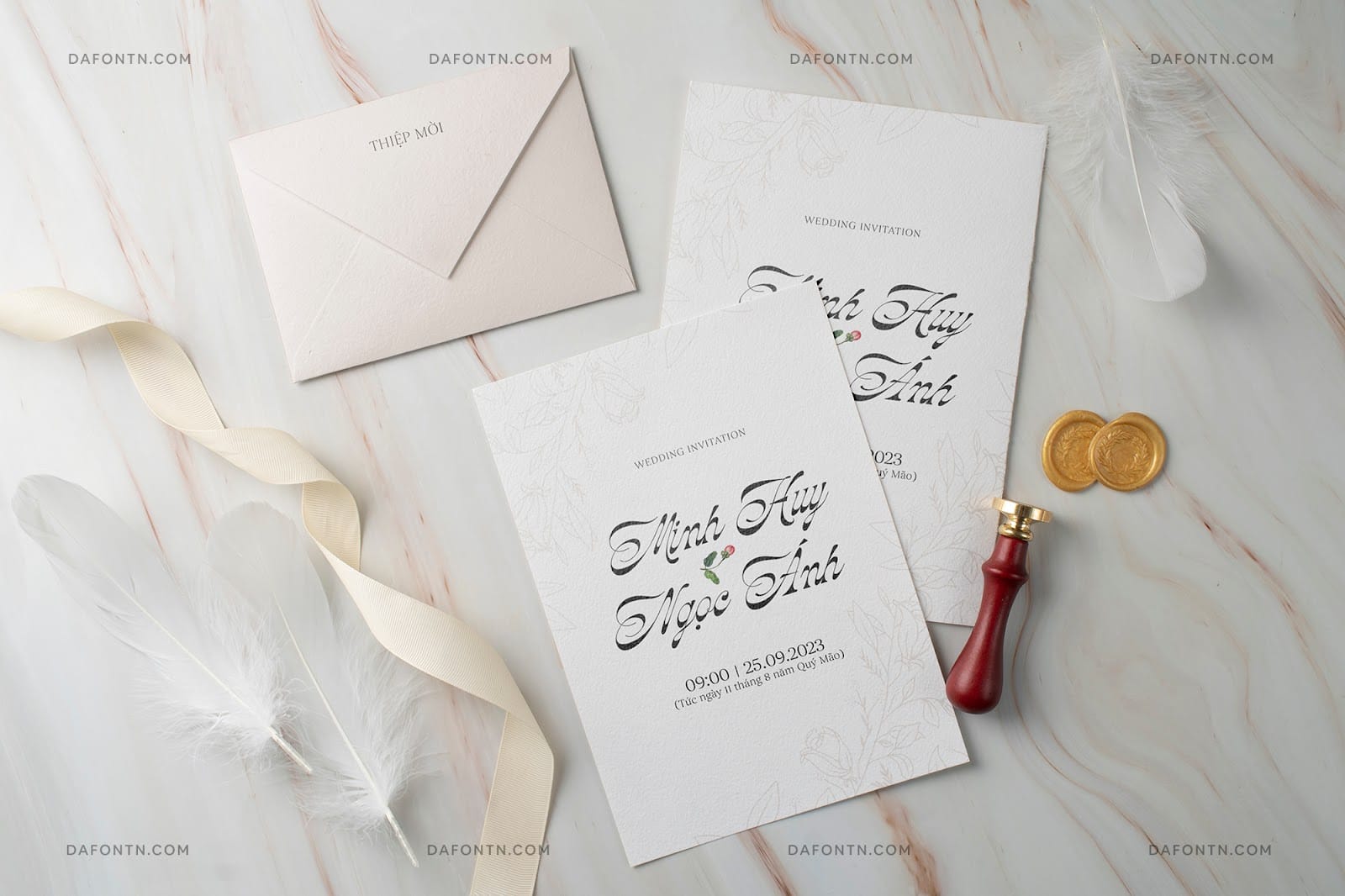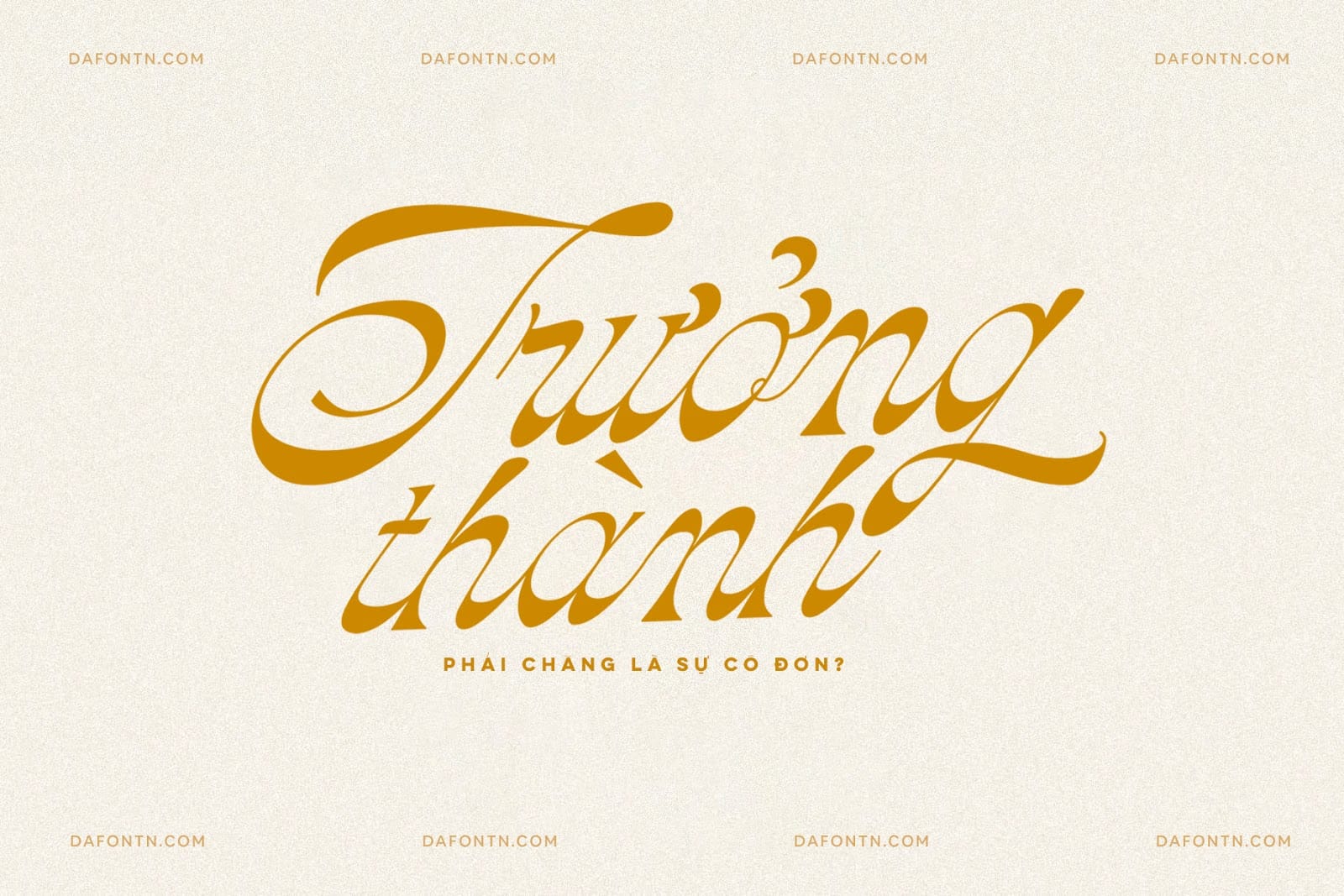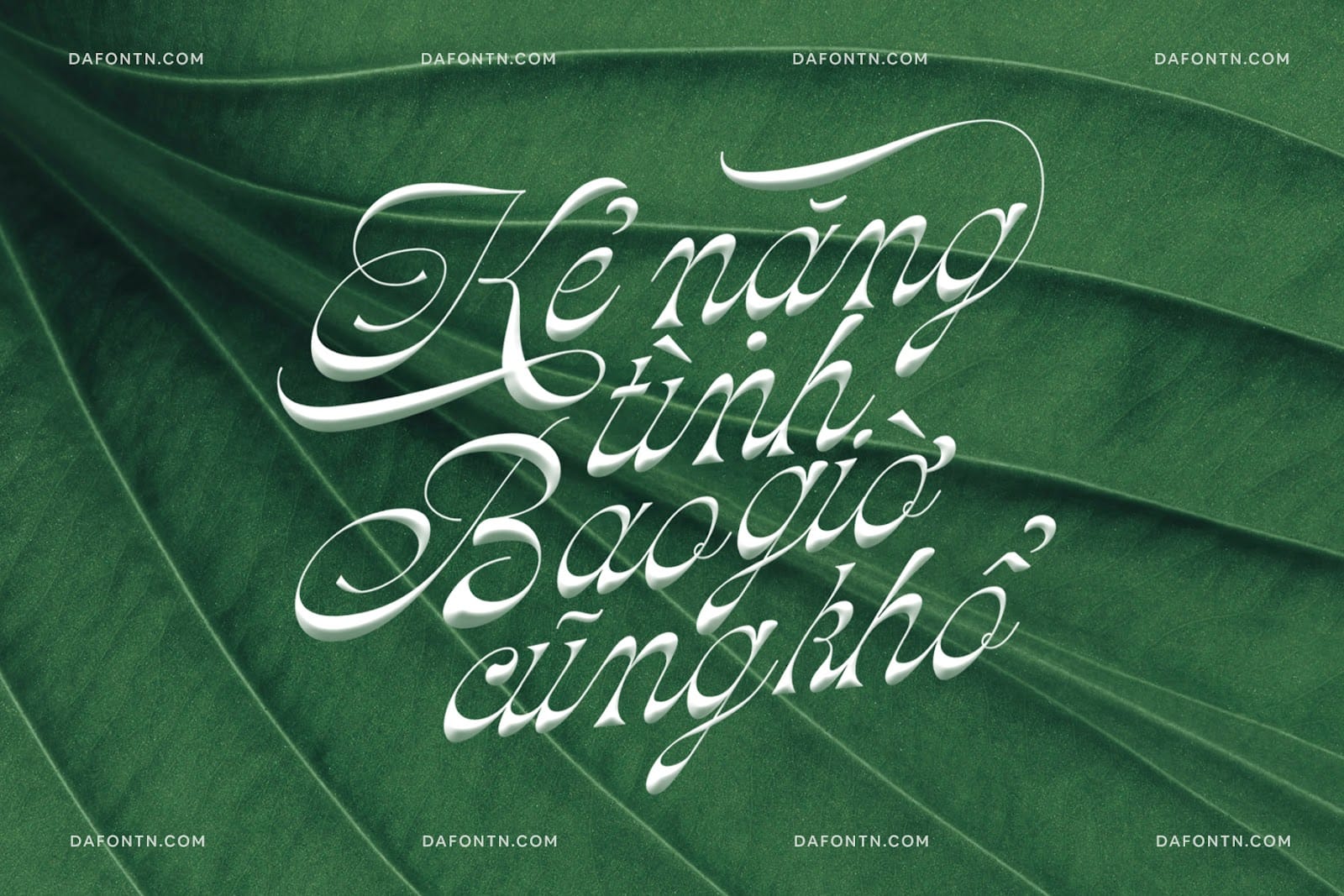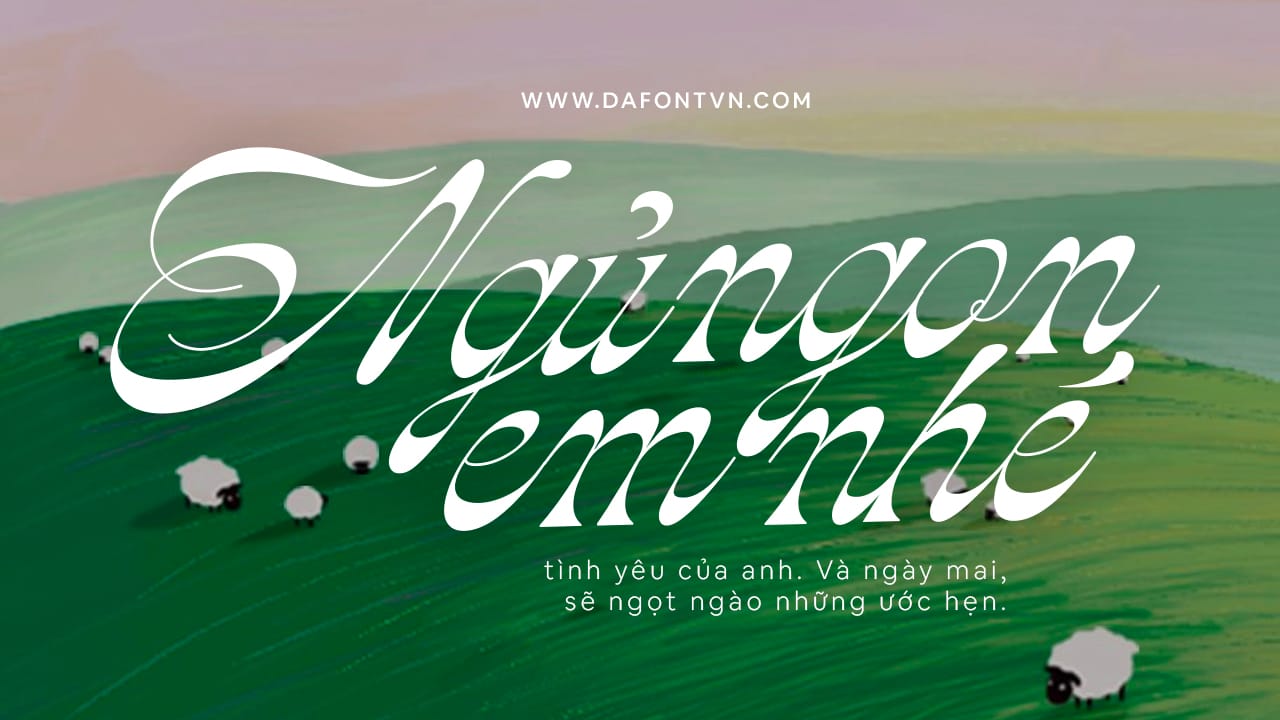
Riverfall Script là một phông chữ viết tay thư pháp đẹp mắt. Kiểu chữ mới này mang đến cảm giác Lofi hoài cổ, tưởng nhớ một thời đại đã qua, font được lấy cảm hứng từ những thiết kế vào những năm thập niên 70. Mặc dù được lấy cảm ứng từ những thiết kế cổ điển nhưng Riverfall Script mang lại một kiểu chữ hoàn toàn hiện đại.
Riverfall Script là sự kết hợp hoàn hảo cho nhiều các thiết kế khác nhau, nó đơn giản và nổi bật khi được sử dụng ở kích thước rất lớn. Bạn có thể sử dụng phông chữ này cho thiệp cưới, áp phích, nhãn hiệu, tạp chí, bìa sách, bao bì hoặc sản phẩm…
Các nét chữ hoa được thiết kế uốn lượn vô cùng ấn tượng và đẹp mắt. Ngoài ra font chữ còn bao gồm hơn 300 ký tự thay thế khác cho cả chữ hoa và chữ thường để bạn có thể tha hồ sáng tạo cho các thiết kế của mình.